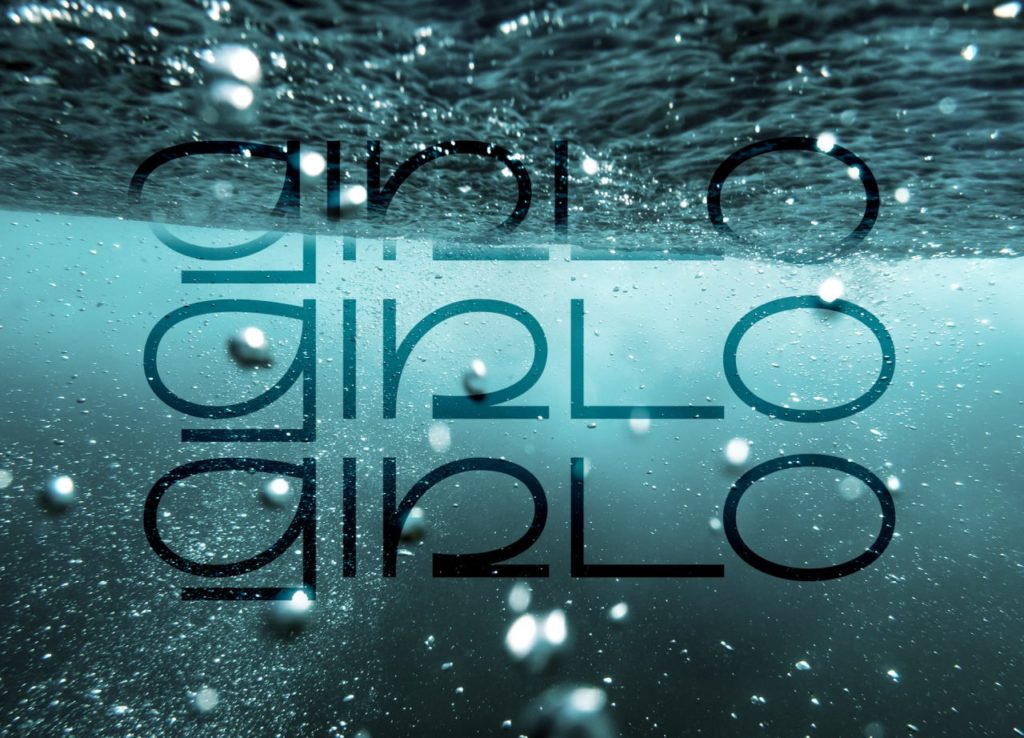
Шрифт Girlo SP
Шрифт Girlo SP — это стильный рукописный шрифт (script), имитирующий свободные мазки кисти или жирного маркера. Его отличительная черта — плавность линий, легкая небрежность и энергичный почерк, который придает надписям динамичный вид. Оригинальная кириллическая версия была создана энтузиастами для того, чтобы этот живописный стиль можно было использовать в русскоязычном дизайне без потери эстетики. Это отличный выбор для создания заголовков и акцентных фраз. Скачать шрифт Girlo SP с поддержкой кириллицы бесплатно можно по ссылке ниже.